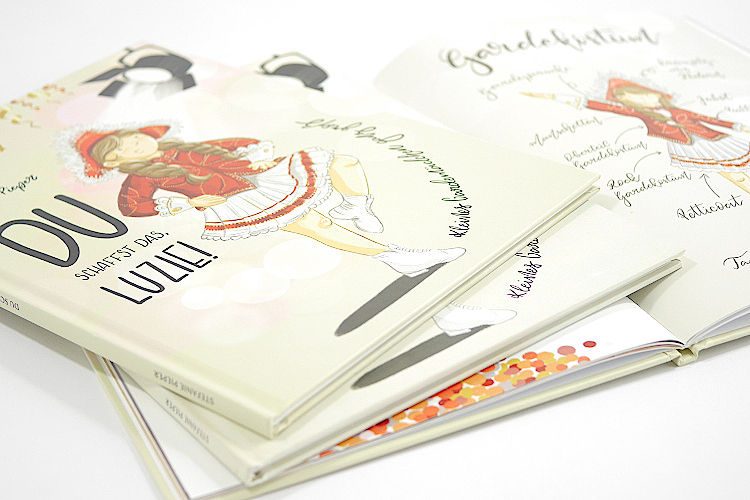
Die Wahl der richtigen Schriftart für ein Kinderbuch ist von entscheidender Bedeutung. Eine gut gewählte Schrift unterstützt das Leseverständnis, wirkt sich positiv auf die Lesefreude aus und passt sich optimal dem Inhalt des Buches an.
Gerade bei Kinderbüchern spielt die Typografie eine wichtige Rolle, da sie nicht nur das Lesen erleichtert, sondern auch die Aufmerksamkeit und das Interesse der jungen Leser fördert. Unterschiedliche Altersgruppen haben unterschiedliche Bedürfnisse: Während Kleinkinder große, einfache Buchstaben bevorzugen, benötigen ältere Kinder Schriftarten, die den Übergang zu komplexeren Texten erleichtern.
Außerdem beeinflusst die Schriftart das gesamte Design und die Gestaltung eines Kinderbuches. Eine passende Schrift kann die Emotionen einer Geschichte unterstreichen und unterstützt die visuelle Wahrnehmung der Kinder. Daher sollten sowohl Überschriften als auch der Fließtext sorgfältig ausgewählt werden, um das bestmögliche Leseerlebnis zu schaffen.
In diesem Artikel erfahren Sie alles Wichtige zum Thema Schriftarten für Kinderbücher und erhalten praktische Tipps, die sich direkt umsetzen lassen. Wir geben Ihnen einen Überblick über beliebte Schriftarten, erklären, welche Fonts sich besonders gut für Kinder eignen, und zeigen Ihnen, worauf Sie bei der Auswahl achten sollten. Zusätzlich erhalten Sie Empfehlungen, wie Sie Ihr Kinderbuch professionell gestalten können – für ein Ergebnis, das Kinder begeistert und zum Lesen motiviert.
In welcher Schriftart sind Kinderbücher geschrieben?
Kinderbücher sind häufig in serifenlosen Schriftarten wie Arial oder Comic Sans geschrieben. Diese Fonts gelten als besonders gut lesbar, da die Buchstaben eine klare Form haben und sich leicht voneinander unterscheiden.
Serifenschriften wie Garamond oder Linotype finden bei Kinderbüchern eher weniger Verwendung, da sie für ungeübte Leser schwieriger zu entziffern sind. Serifenschriften eignen sich besser für Fließtexte in Büchern für ältere Kinder oder Erwachsene.
Die Gestaltung eines Kinderbuches berücksichtigt nicht nur die Lesbarkeit, sondern auch die Typografie, das Design und die Gestaltung der Seiten. Verspielte Fonts kommen oft bei Überschriften oder in Bildern zum Einsatz, während der Fließtext in einer einfachen, gut lesbaren Schriftart geschrieben wird.
Welche Schriftart können Kinder gut lesen?
Für Kinder sind serifenlose Schriftarten am besten geeignet. Diese Fonts erleichtern das Lesen, weil die Buchstaben einfacher zu erkennen sind. Beispiele hierfür sind:
- Comic Sans: Obwohl diese Schriftart in anderen Kontexten umstritten ist, eignet sie sich hervorragend für Kinderbücher. Sie wirkt freundlich, leicht und ist für Kinder gut lesbar.
- Arial: Diese serifenlose Schriftart ist klar strukturiert und wird häufig in Schulbüchern verwendet.
- Sassoon Primary: Entwickelt speziell für den Erstleseunterricht. Diese Schriftart unterstützt Kinder beim Erlernen der Buchstabenformen.
Die Schriftgröße spielt ebenfalls eine wesentliche Rolle. Größere Buchstaben sind einfacher zu erkennen und verringern die Ermüdung beim Lesen. Auch der Zeilenabstand sollte großzügig gewählt werden, damit das Auge den Text leichter erfassen kann.
Was ist die beste Schriftart für ein Buch?
Die beste Schriftart hängt vom Thema, Design und Zweck des Buches ab. Für ein Kinderbuch sind folgende Punkte entscheidend:
- Lesbarkeit: Die Schrift muss einfach und schnell zu erfassen sein.
- Design: Die Schriftart sollte zum Inhalt passen und das kreative Design des Buches unterstützen.
- Zweck: Handelt es sich um ein Vorlesebuch oder um ein Buch für Selbstleser?
Beispiele geeigneter Fonts:
- Comic Sans: Ideal für kürzere Texte und kindgerechte Themen.
- Arial: Perfekt für den Fließtext, da sie neutral und gut lesbar ist.
- Garamond: Geeignet für etwas ältere Kinder, die bereits gut lesen können.
Auch die Nutzungsbedingung der Schriftart ist wichtig. Kostenlose Downloads sind online verfügbar, jedoch sollte auf das Urheberrecht geachtet werden.
Welche Schriftart wird in Schulbüchern verwendet?
In Schulbüchern werden häufig serifenlose Schriftarten wie Arial oder Helvetica verwendet. Diese Fonts sind international anerkannt und unterstützen das Lernen durch ihre klare Struktur.
Wichtige Merkmale:
- Einfachheit: Die Buchstabenformen lassen sich leicht unterscheiden.
- Konsistenz: Einheitliche Schriftgrößen und Schriftarten für bessere Lesbarkeit.
- Didaktische Funktion: Schriftarten wie Sassoon Primary sind speziell für Lernzwecke entwickelt.
Fazit
Die Wahl der richtigen Schriftart für ein Kinderbuch beeinflusst maßgeblich, wie Kinder das Buch wahrnehmen und lesen. Serifenlose Schriften wie Arial oder Comic Sans eignen sich besonders gut.
Achten Sie auf eine angemessene Schriftgröße, Zeilenabstände und ein durchdachtes Design.